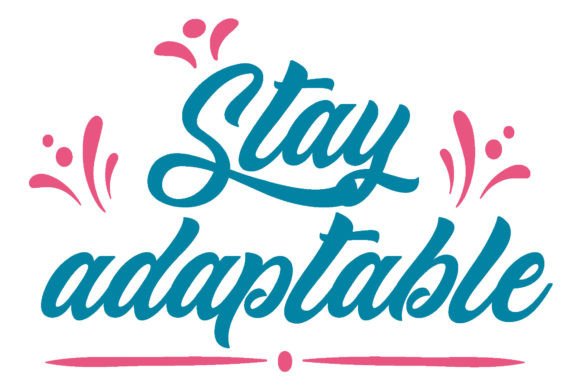
Stay Adaptable Quotes Design
Ulasan Lengkap: Stay Adaptable Quotes Design
Se você está em busca de um recurso criativo que una inspiração e versatilidade, o Stay Adaptável Quotes Design chegou para transformar seus projetos. Este pacote digital oferece tudo o que designers, empreendedores e criadores de conteúdo precisam para produzir peças impactantes, sem perder a mensagem de adaptação e resiliência.
Mensagem inspiradora: A frase “Stay Adaptable” (Mantenha‑se Adaptável) ressoa com profissionais modernos que precisam se reinventar constantemente, adicionando valor emocional às suas criações.
Por que escolher este design?
Além da qualidade técnica, este pacote se destaca pelo design minimalista e moderno que combina perfeitamente com branding contemporâneo, mood boards, capas de e‑books, apresentações corporativas e material de marketing digital. A combinação de tipografia elegante e elementos gráficos discretos garante que a mensagem seja o centro das atenções.